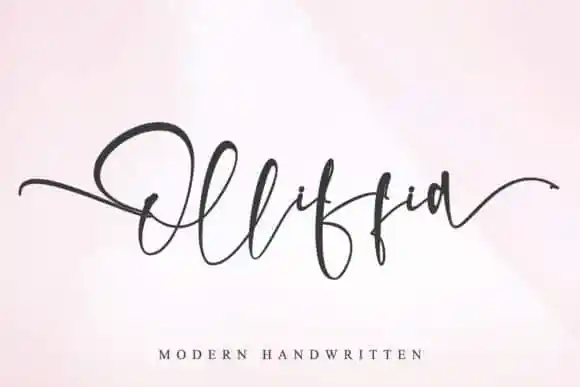
Olliffia Calligraphy Font – Download Grátis
A Olliffia Calligraphy Font é uma escolha perfeita para aqueles que buscam uma mistura suave entre modernidade e personalidade. Ela foi criada pelo designer Thomas Aradea com um ar de elegância e delicadeza, característica típica dos fontes script. Essa fonte não só dá um toque autêntico a qualquer design, mas também adiciona uma dose extra de originalidade. Olliffia é perfeita para aqueles buscando uma fonte de escrita cursiva que vai além do básico. Ela se destaca por seu estilo moderno e encantador, oferecendo um grau significativo de personalização através dos seus detalhes finos, alternativas de caracteres e ligaturas especiais. A Olliffia é PUA codificada, permitindo que você acesse todos os caracteres delicados e gílos de maneira simples e intuitiva. Com o PUA encoding, não há mais problemas com caracteres desconhecidos ou perdidos em certos sistemas de texto. Isso significa que seu design pode ser ainda mais único e expressivo. Olliffia é uma fonte script perfeita para qualquer tipo de aplicação visual – seja um layout editorial, embalagens de produtos, arte digital ou até mesmo materiais gráficos online. Sua versão com características especiais faz dela o complemento ideal que você precisa para dar vida a qualquer projeto criativo.